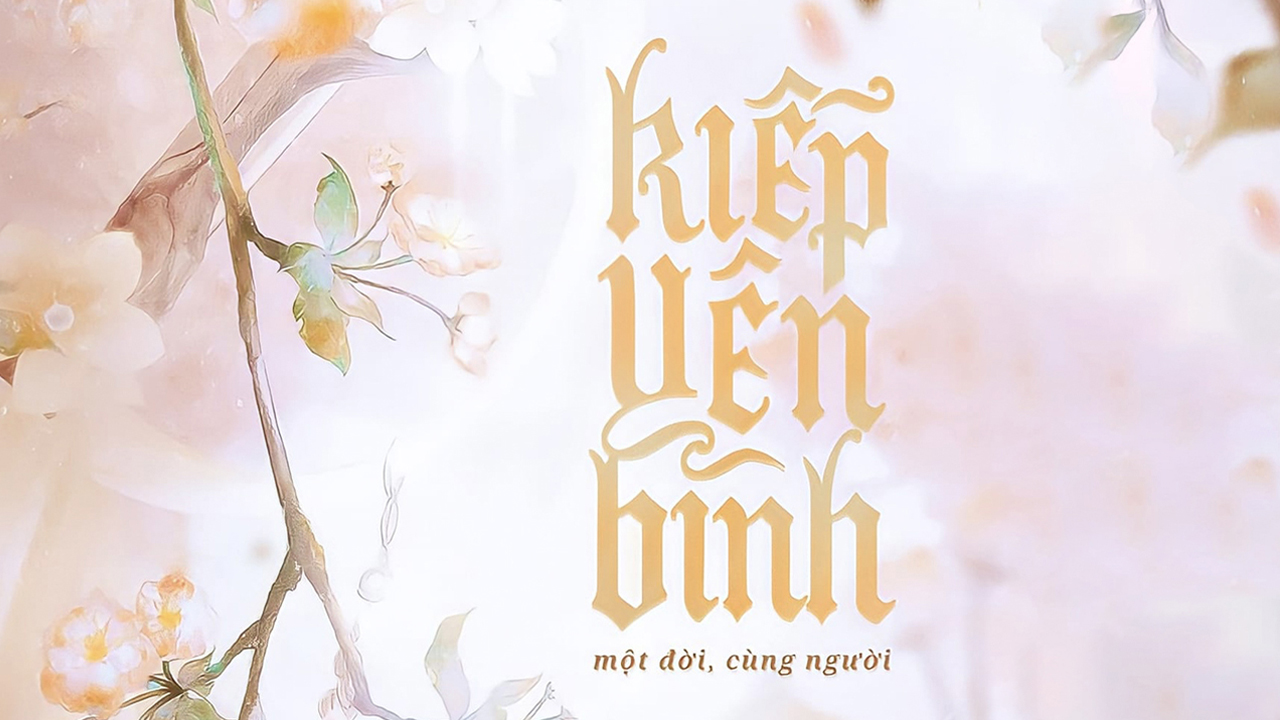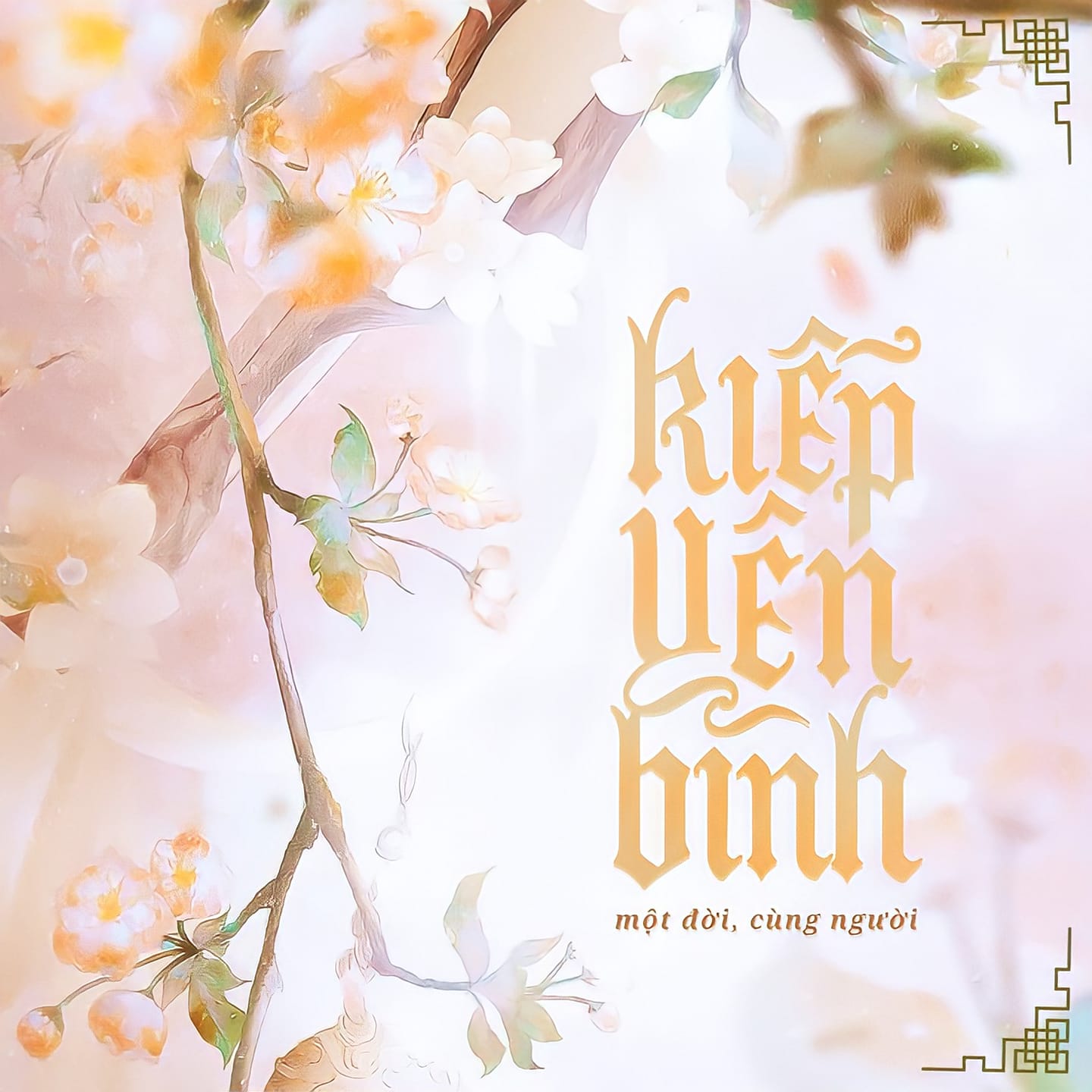
Font Anglican Text Việt Hóa siêu đẹp
Font Anglican Text Việt Hóa là font chữ mang hơi hướng của các chữ Latinh cổ ngày xưa rất phù hợp cho các thiết kế cổ trang, bìa sách, typo hoặc bất kỳ thiết kế nào cần sự cổ điển, cứng cáp. Font đã được Việt Hóa đầy đủ, kerning và tối ưu lại một số chi tiết so với font gốc.